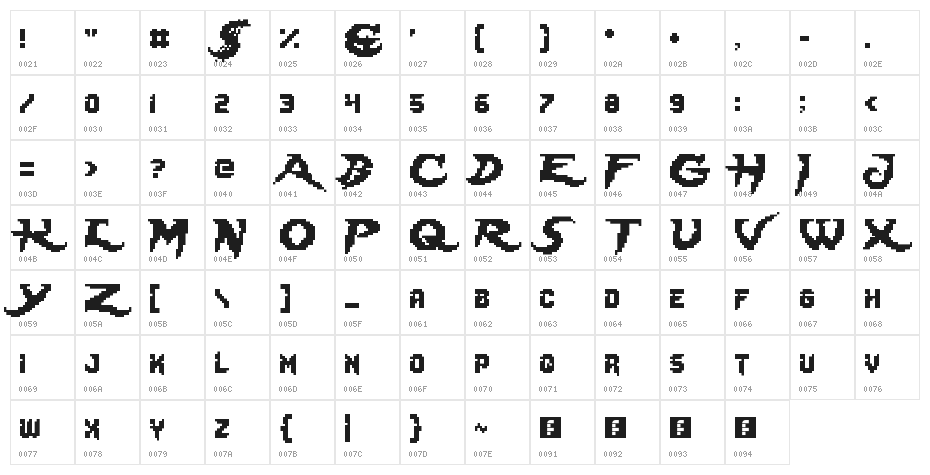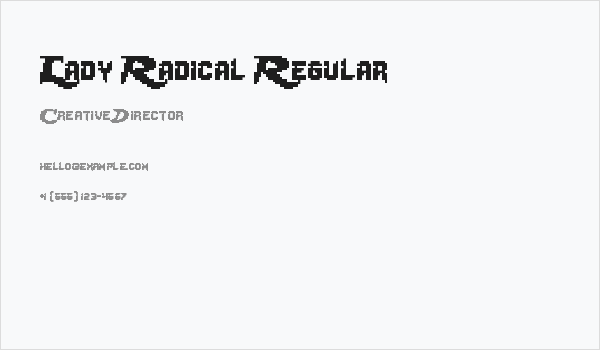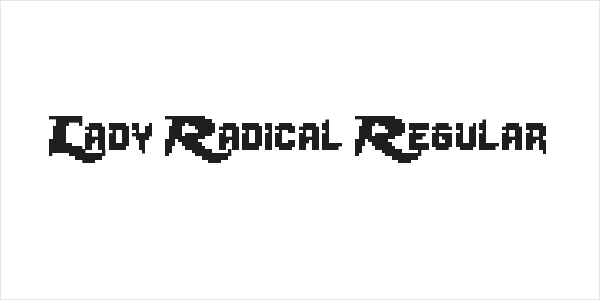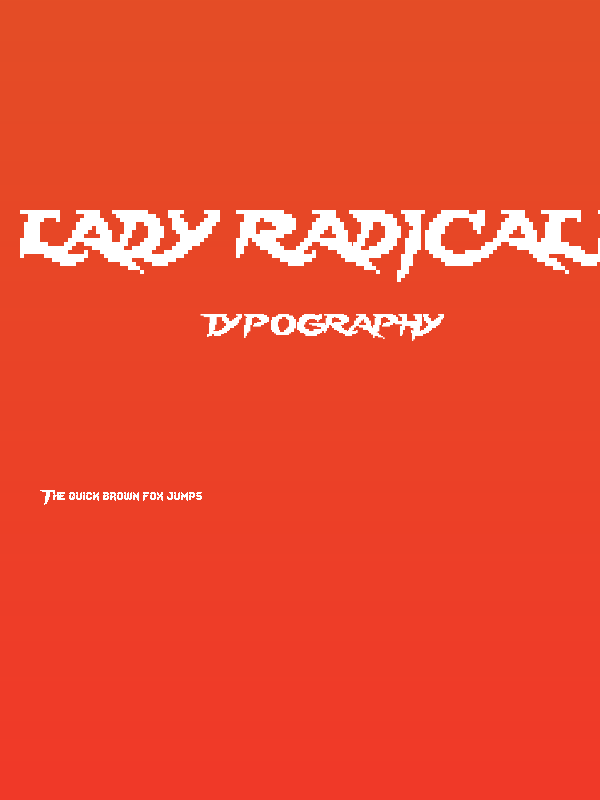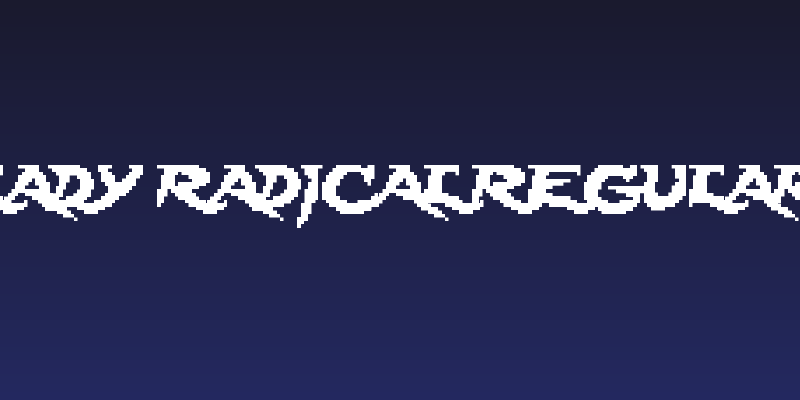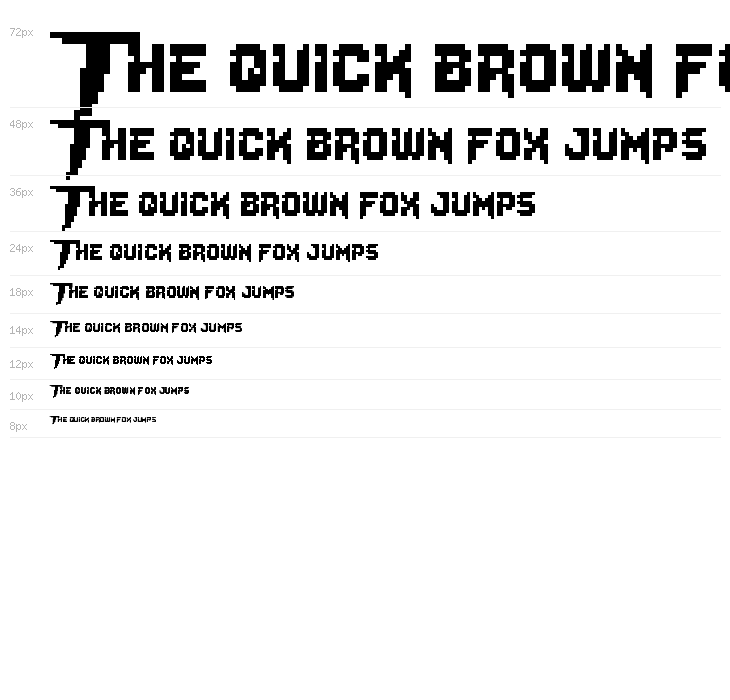
Lady Radical Regular Font
✎ Thick
| 整体风格 | Modern, Edgy |
| 推荐项目 | Ideal for music album covers, event posters, video game titles, and branding for edgy or alternative products. |